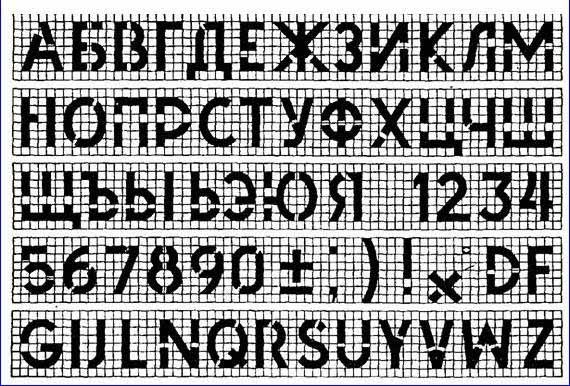
Как сделать трафареты букв в word?
Вопрос о том, как сделать трафарет в программе Microsoft Word, интересует многих пользователей. Проблема в том, что найти на него вменяемый ответ на просторах интернета не так уж и просто. Если и вас интересует эта тема, вы обратились по адресу, но для начала давайте разберемся, что представляет собой трафарет.
Трафарет — это «продырявленная пластинка», по крайней мере, таково значение этого слова в точном переводе с итальянского. Кратко о том, как сделать такую «пластинку» мы расскажем во второй половине этой статьи, а непосредственно ниже мы поделимся с вами тем, как создать основу для традиционного трафарета в Ворде.
Выбор шрифта
Если вы готовы серьезно заморочиться, параллельно подключив фантазию, для создания трафарета вполне можно использовать любой шрифт, представленный в стандартном наборе программы. Главное, когда он будет распечатан на бумаге, сделать перемычки — места, которые не будут вырезаться в буквах, ограниченных контуром.
Собственно, если вы готовы так попотеть над трафаретом, непонятно, зачем вам наша инструкция, так как в вашем распоряжении есть все шрифты MS Word. Выбираете понравившийся, пишите слово или набираете алфавит и печатаете на принтере, а затем вырезаете их по контуру, не забывая о перемычках.
Если же вы не готовы тратить столько сил, времени и энергии и трафарет классического вида вас вполне устраивает, наша с вами задача — найти, скачать и установить тот самый классический трафаретный шрифт. От изнурительного поиска мы готовы вас избавить — мы все нашли самостоятельно.
Шрифт Trafaret Kit Transparent полностью имитирует старые добрые советские трафареты ТШ-1 с одним приятным бонусом — помимо русского языка в нем есть еще и английский, а также ряд других символов, отсутствующих в оригинале. Скачать его можно сайта автора.
Создание основы для трафарета
Выберите Trafaret Kit Transparent из списка доступных в Ворде шрифтов и создайте в нем нужную надпись.
Если же вам нужен алфавитный трафарет, напишите на странице документа алфавит. По необходимости можно добавить и другие символы.
Стандартная книжная ориентация листа в Ворде — не самое подходящее решение для создания трафарета. На альбомной странице он будет смотреться более привычно. Изменить положение страницы поможет наша инструкция.
Теперь текст нужно отформатировать. Задайте подходящий размер, выберите подходящее положение на странице, установите достаточные отступы и интервалы, как между буквами, так и между словами. Наша инструкция поможет вам все это сделать.
Возможно, стандартного формата листа А4 вам будет недостаточно. Если вы хотите изменить его на больший (A3, к примеру), наша статья поможет вам это сделать.
Примечание: Изменяя формат листа, не забывайте соразмерно изменить размер шрифта и сопутствующие параметры.
Не менее важными в данном случае являются возможности принтера, на котором трафарет будет распечатываться — поддержка выбранного формата бумаги обязательна.
Печать трафарета
Создание трафарета
Как вы понимаете, толку от трафарета, распечатанного на обычном листике бумаги, практически никакого. Больше одного раза им вряд можно будет воспользоваться. Именно поэтому распечатанную страницу с основой для трафарета необходимо «укрепить». Для этого вам понадобится следующее:
- Картон или полимерная пленка;
- Копирка;
- Ножницы;
- Сапожный или канцелярский нож;
Распечатанный текст необходимо перевести на картон или пластик.
В случае перевода на картон, сделать это поможет обычная копирка (копировальная бумага). Страницу с трафаретом нужно просто наложить на картон, разместив между ними копирку, а затем обвести контур букв карандашом или ручкой. Если копировальной бумаги нет, можно продавить контуры букв ручкой. Аналогичное можно проделать и с прозрачным пластиком.